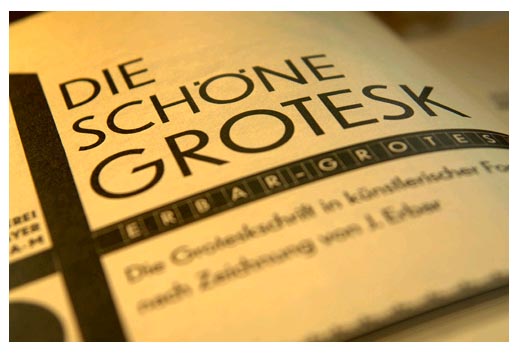
Jakob Erbar
Erbar
Jakob Erbar foi o autor da fonte Erbar Grotesk, uma sem serifa que terá servido de modelo à Futura de Paul Renner.
Dentro do revivalismo das Egípcias no século XX, aparece em 1936 a fonte Candida de Jakob Erbar, desenhada para a Fundição Ludwig & Meyer. O carácter de serifa-grossa é bem mais pronunciado que na Clarendon, a fonte que serviu de modelo a Jakob Erbar.